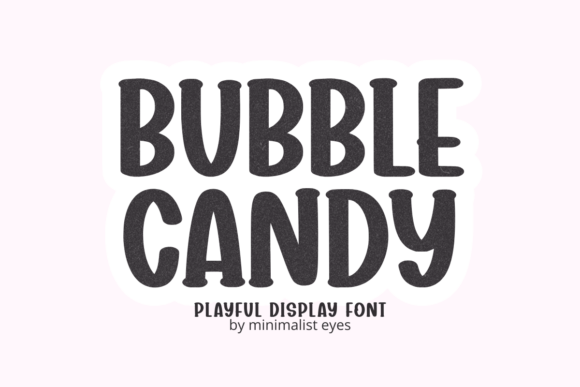
Bubble Candy
Mencari elemen reka bentuk yang sesuai boleh menjadi mencabar, tetapi Bubble Candy menawarkan koleksi luar biasa yang menaik taraf karya anda serta-merta.
Sama ada anda mencipta produk POD (Print on Demand), jemputan perkahwinan atau grafik media sosial, Bubble Candy amat bersesuaian.